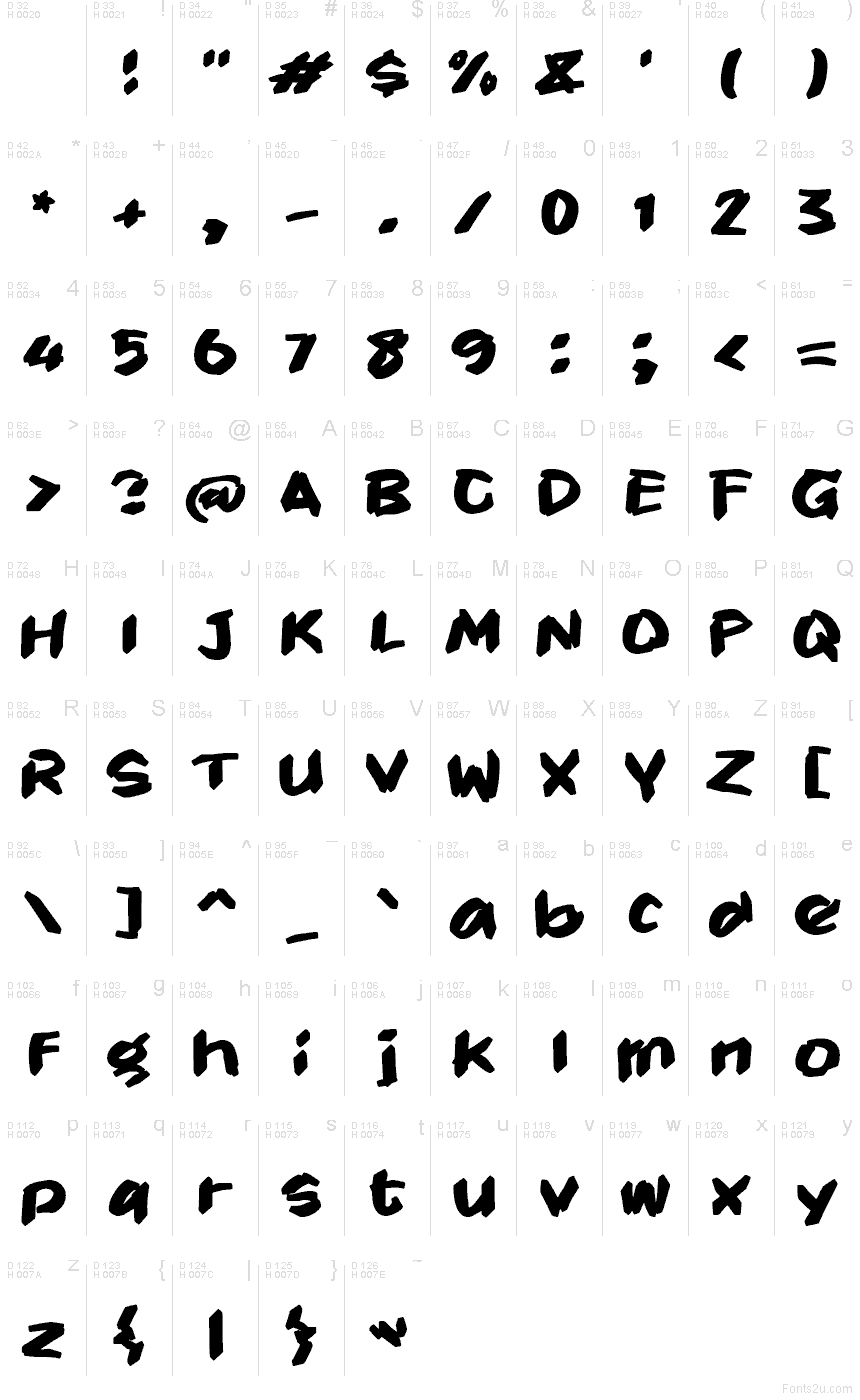
Vabrosta od Wep je bezplatné písmo typu brush, které definují široké tahy štětcem a ostře řezané hrany, díky nimž si písmena zachovávají syrový, nikoliv fluidní vzhled. Rytmus působí ručně tesaným dojmem a má svou váhu – zaoblené vnitřní prostory kontrastují s náhlými rohy, což celému designu dodává úderný, plakátový vzhled.
Tato kombinace dynamického pohybu štětce a masivních bloků skvěle funguje na hudebních letácích, streetwearových grafikách, plakátech na akce, obalech a krátkých nadpisech na sociálních sítích, kde by uhlazené skriptové písmo působilo až příliš jemně. Vabrosta může také posloužit jako základ pro loga nebo nadpisy, které potřebují ručně vyrobený charakter s dostatečnou dávkou drsnosti, aby obstály jako samostatný grafický prvek, nejen jako pouhý text.
Vabrosta
Prezentace a vizuální ukázka písma Vabrosta
Mapa znaků písma Vabrosta
Mapa znaků písma Vabrosta: Základní latinka, strana 1
Glyfy písma Vabrosta — Základní latinka, strana 1